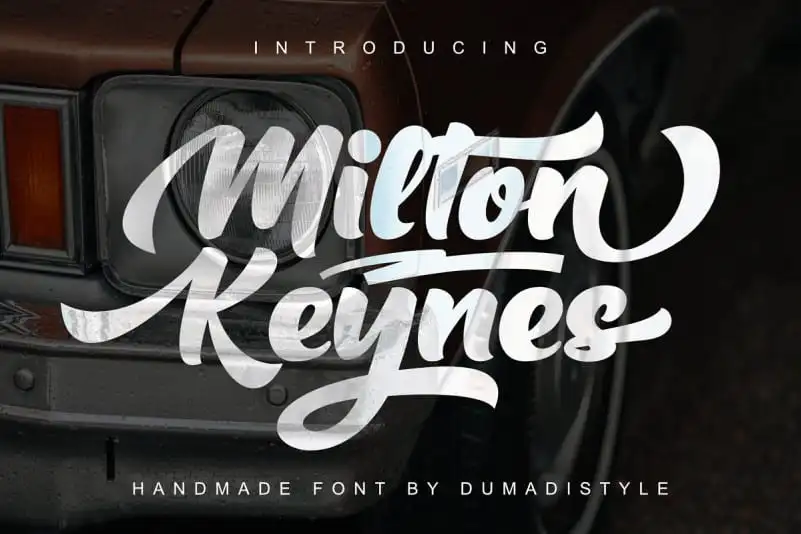
Milton Keynes Script Font – Download Grátis
Introduzimos a Milton Keynes Script Font – uma nova tipografia cuidadosamente criada com curvas arredondadas elegantes, característica de tipo de script que traz personalidade. Especialmente projetado para aplicar em diferentes formatos de mídia, como logos de marca, camisetas desenhadas, cartazes, cartões de visita, tipografia e jornais, Milton Keynes é uma fonte espessa moderna inspirada nas raspuras feitas a mão. Com suas curvas perfeitamente equilibradas e fortes linhas, esta fonte de tipo script se destaca por seu caráter distintivo, tornando-a ideal para trabalhos de design. Devido à sua natureza espessa, é especialmente adequada para aplicar em elementos visuais que exigem uma forte presença visual, como logos ou cartões de visita de marcas. Seja você um designer gráfico experiente ou um iniciante, Milton Keynes oferece um jeito novo e atraente de adicionar personalidade aos seus projetos. Além disso, sua natureza espessa também a torna uma excelente escolha para trabalhos que exigem um estilo sólido e duradouro em elementos como cartazes ou publicações impressas. Composto a partir das raspuras feitas a mão de designers experientes, a Milton Keynes Script Font é uma ótima opção para quem busca estilos criativos sem abandonar o poder do design gráfico tradicional.